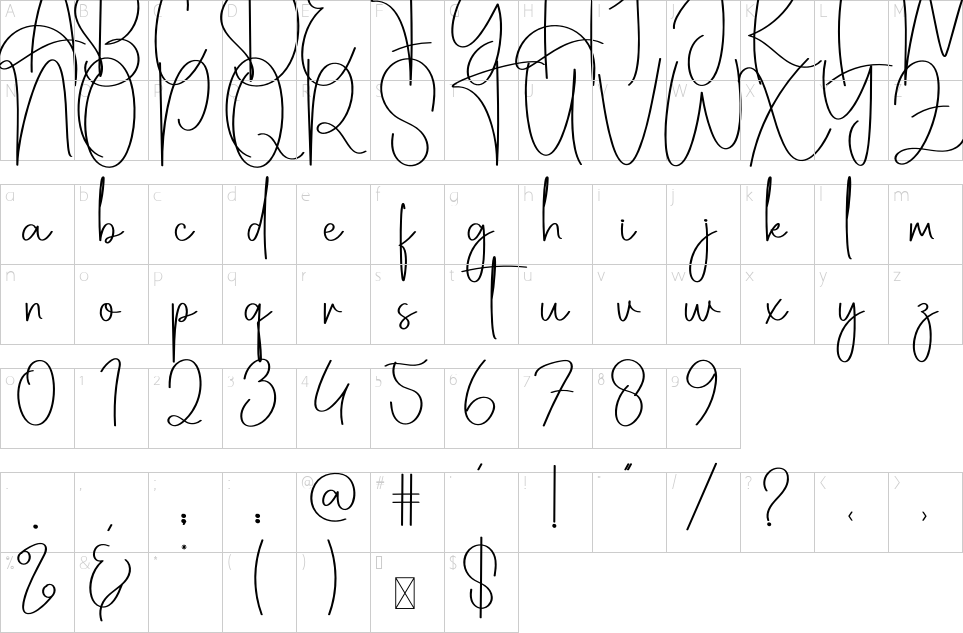
Descubra a fonte Scaryday, uma elegante e inovadora opção para criar designs assustadores e impactantes. Desenvolvida pelo designer scratchones, Scaryday é uma fonte que combina elementos de horror e modernidade, ideal para aplicar em websites de notícias, postagens no Instagram ou qualquer projeto que precise de uma fonte única e intrigante. Com uma design moderno e versátil, Scaryday é fácil de usar e torna suas criações únicas, deixando um efeito impressionante em qualquer projeto. Recomendado para todos aqueles que valorizam uma fonte com um toque sinistro para suas publicações, Scaryday está disponível em versões para Windows e Mac. Sua facilidade de uso e grande número de downloads são testemunhas de sua popularidade e qualidade. Aproveite o download gratuito desta fonte assustadora e personalize seu design como nunca antes.